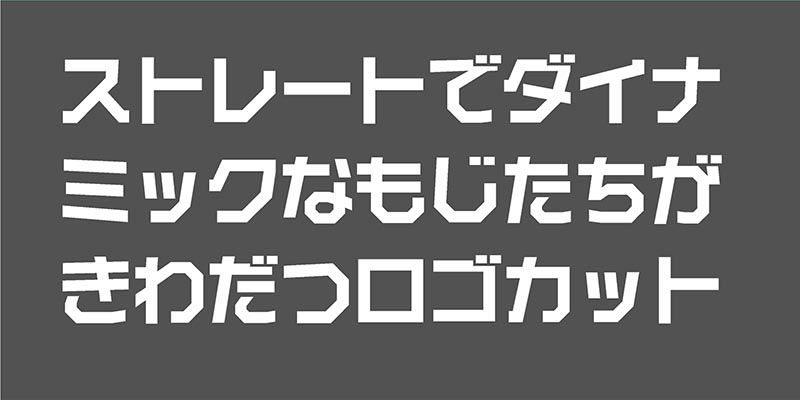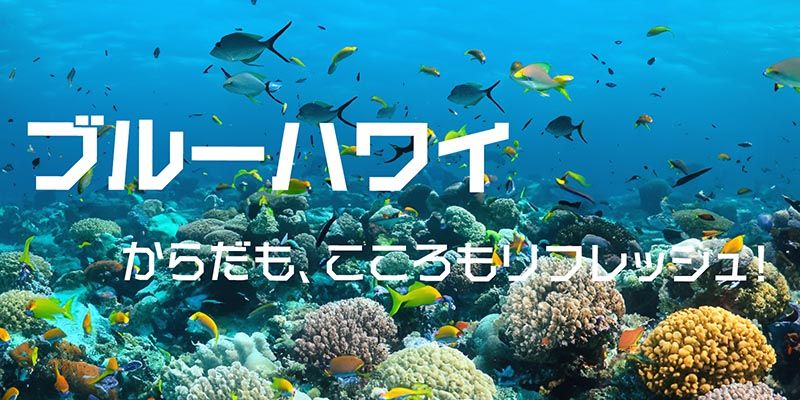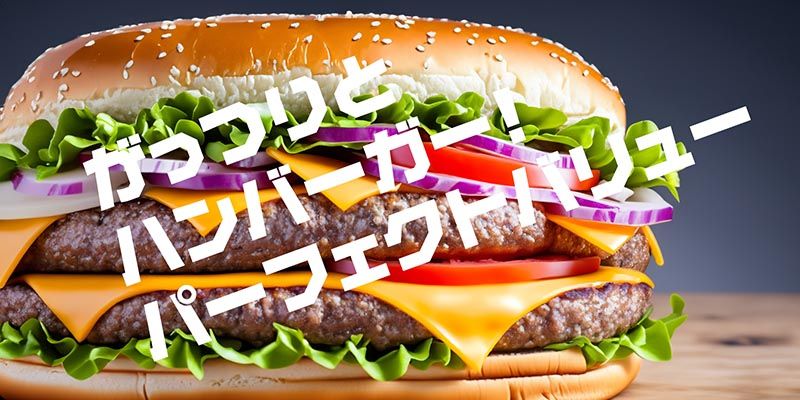
Anfang der Neunzigerjahre veröffentlichte Adobe die Kamono Kana-Serie. Sie besteht aus drei reinen Kana-Schriftfamilien: Logo Line, Logo Arl und Logo Cut. Heute sind die Kamono Kana-Schriftfamilien in Adobe Fonts verfügbar.
Logo Cut greift das einheitliche, klare Design und die Leichtigkeit von Logo Line auf. Da die Buchstabenformen jedoch überwiegend aus geradlinigen Elementen bestehen, ist die Schrift visuell außergewöhnlich scharf und prägnant. Sie ist in vier Schriftstärken erhältlich und eignet sich sowohl für Beschilderungen als auch für eine Vielzahl anderer Anwendungen.
Kamono Design Laboratory wurde 1978 von dem japanischen Schriftdesigner Minoru Kamono (鴨野 実) gegründet. Das Design-Studio hat zahlreiche hochwertige japanische Schriften entworfen. Minoru Kamono hatte das Ziel, ansprechende Schriften zu kreieren, die weich und doch ausdrucksstark sind.